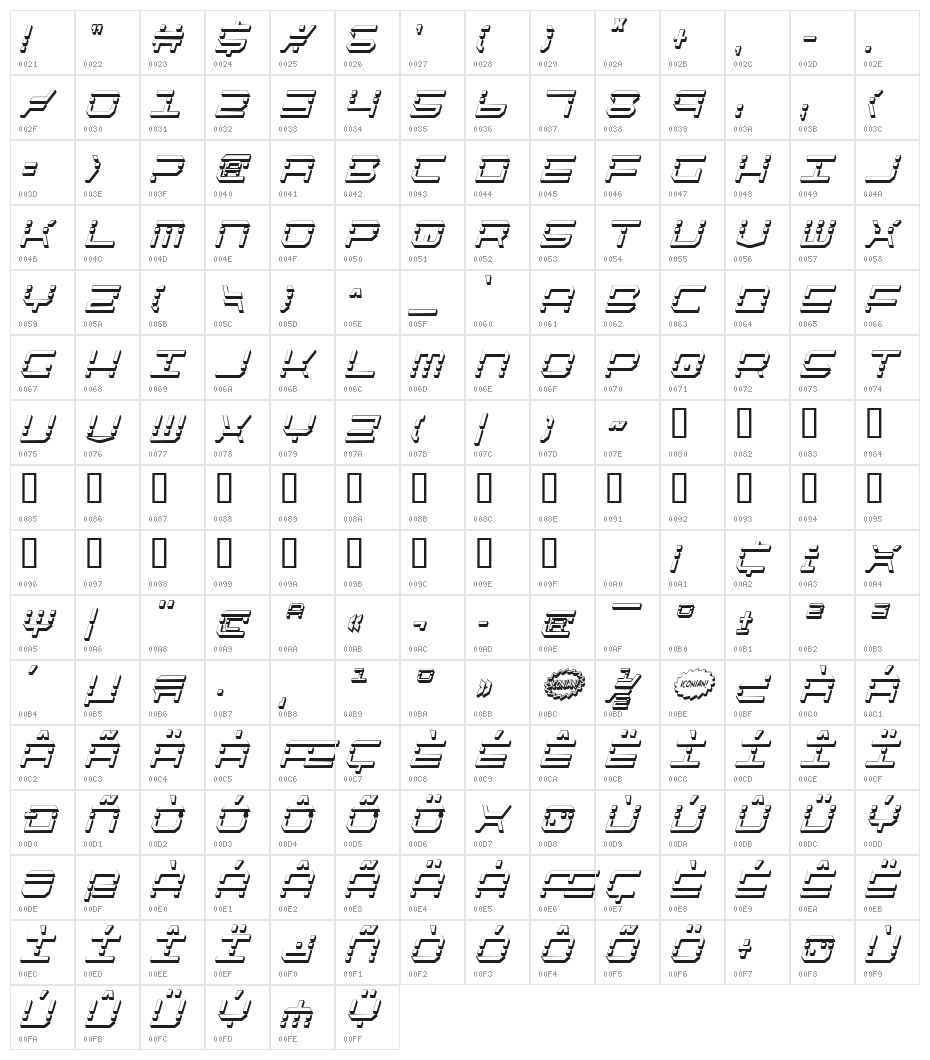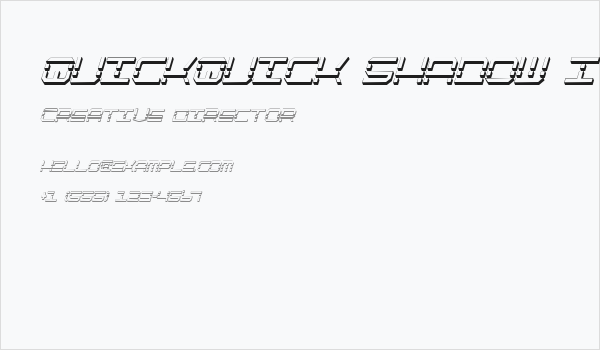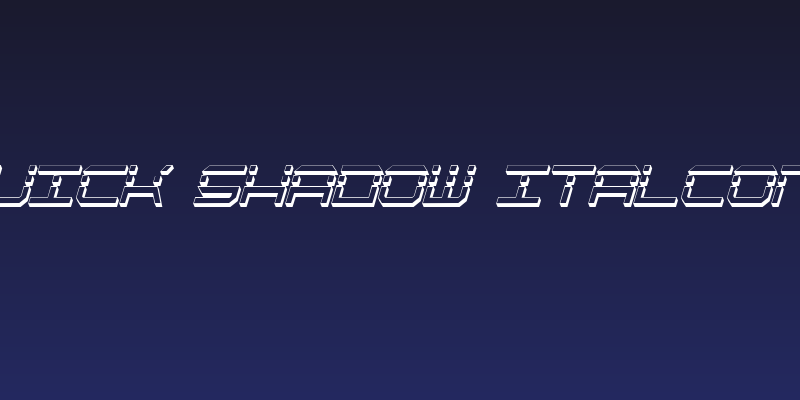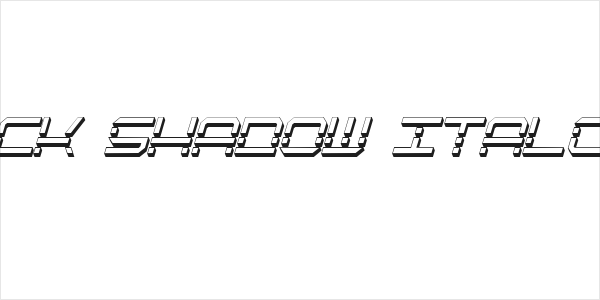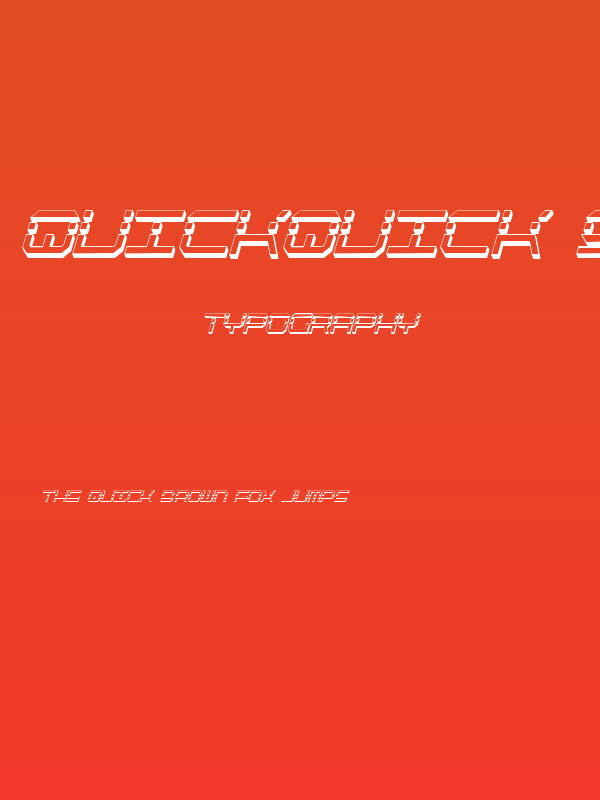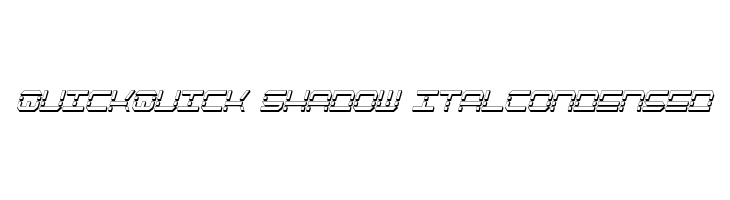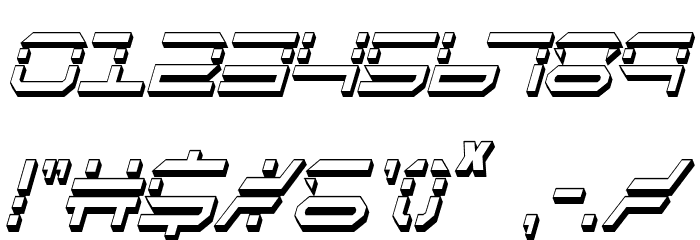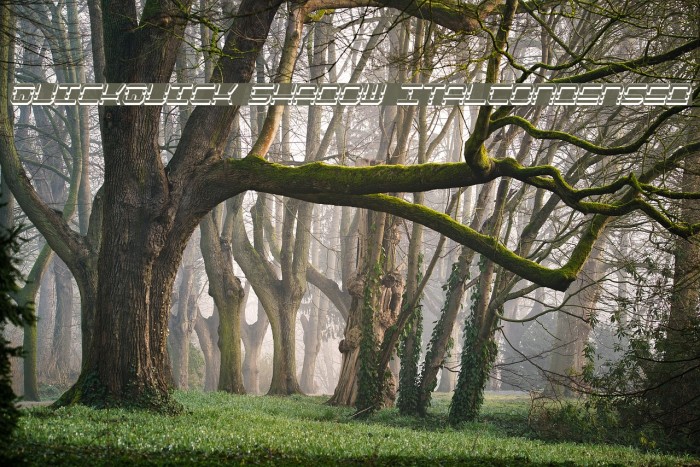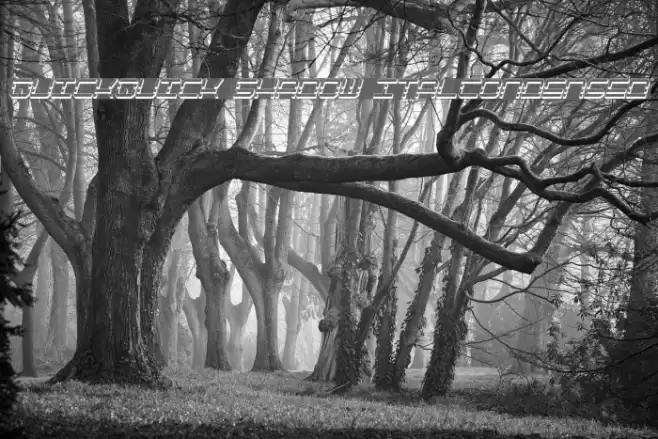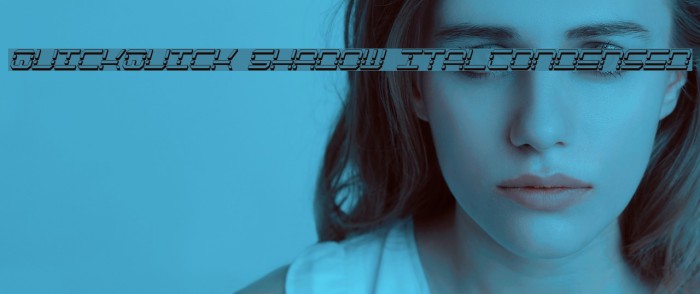
QuickQuick Shadow ItalCondensed Font
| Projets proposés | Ideal for futuristic branding, tech-related projects, video game titles, and modern poster designs. |